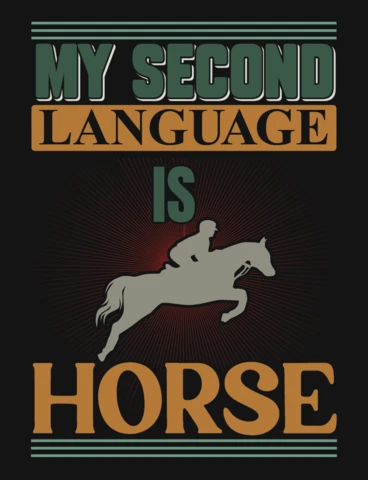
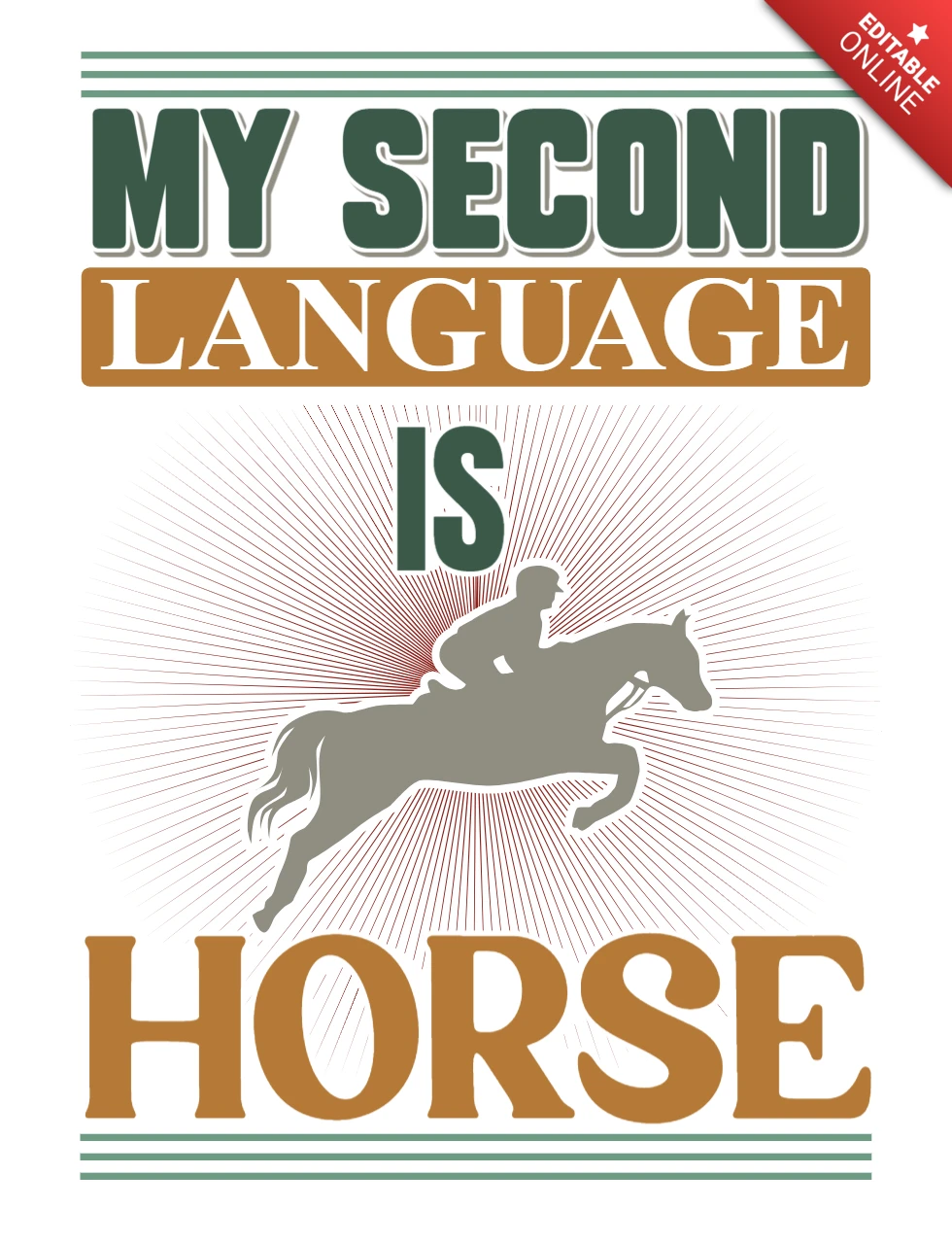
Modèle de typographie vintage : 'ma deuxième langue est le cheval' graphique modifiable
Éditer dans Design Studio Télécharger en JPGDonnez libre cours à votre passion pour les sports équestres avec notre modèle de conception modifiable présentant une typographie vintage et une citation humoristique : "ma deuxième langue est le cheval", parfaite pour les produits dérivés !